1.意象替代
汉字最早是由象形发展而来,通过线条描述物体的外形特征达到表述的目的。我们设计字体时可以反其道而行之,根据字意将字的某个笔画或部件用具体的图形/图像代替,达到直观表达字意的效果。
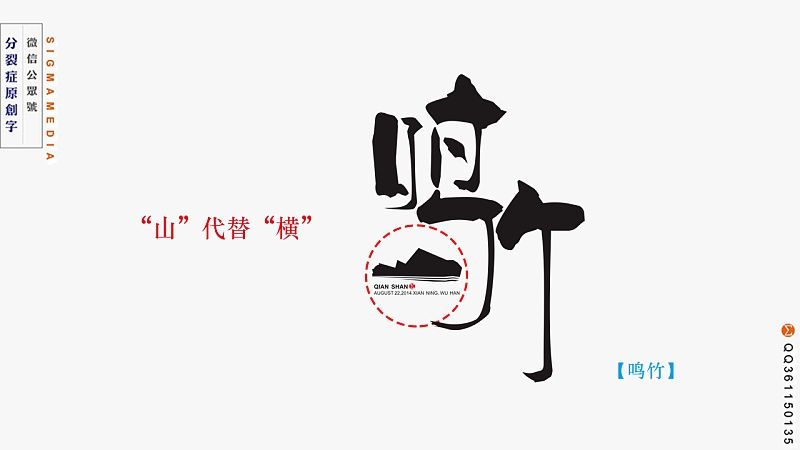
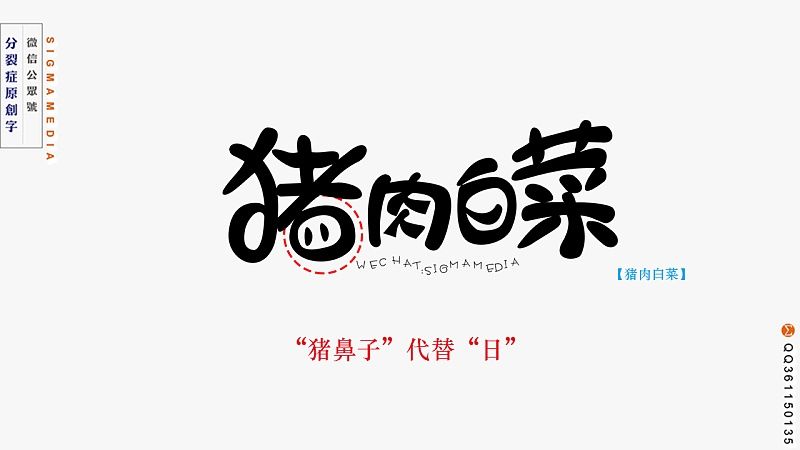
2.笔体重复
设计了几个字却感觉貌合神离很难搭在一起?这时宜用此招,笔体重复就是在几个字中都使用同一种笔体,或是找到某个视觉效果显著的特点重复用在不同的字中。
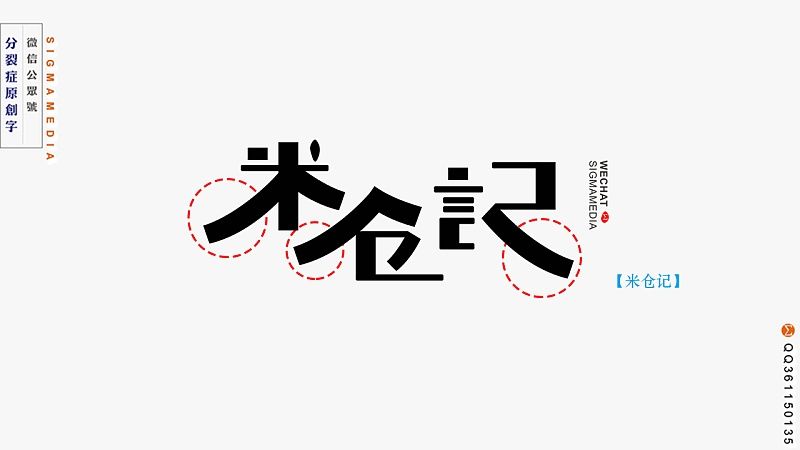
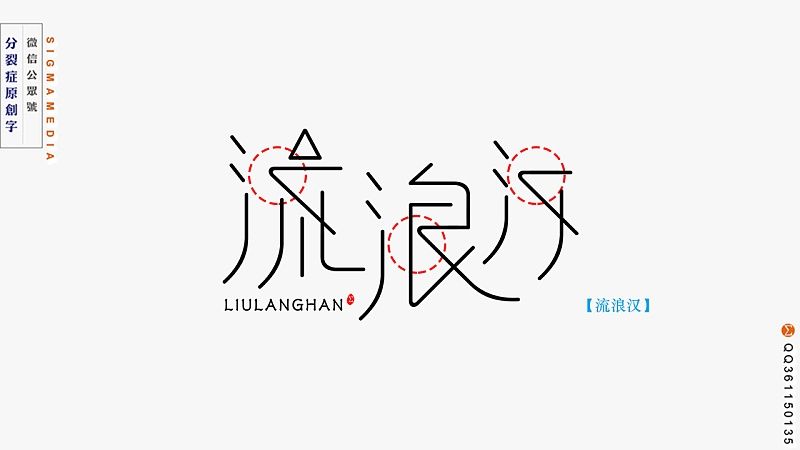
笔体重复可以让字秩序化、整齐化,整体视觉呈现出和谐统一、富有韵律的效果,这招重点是设计前先找到几个字的共同点。
3.粗细对比
都说没有对比就没有伤害,可见对比能够造成冲突,引起关注。汉字是方块字,横竖的笔画自然是非常之多,通过横变粗竖变细或横变细竖变粗,夸大横竖笔画的粗细对比能够让字风格独特出人意料。
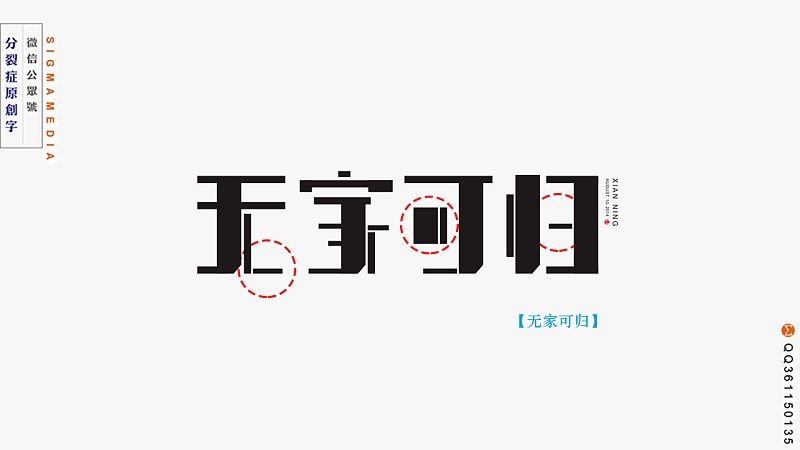
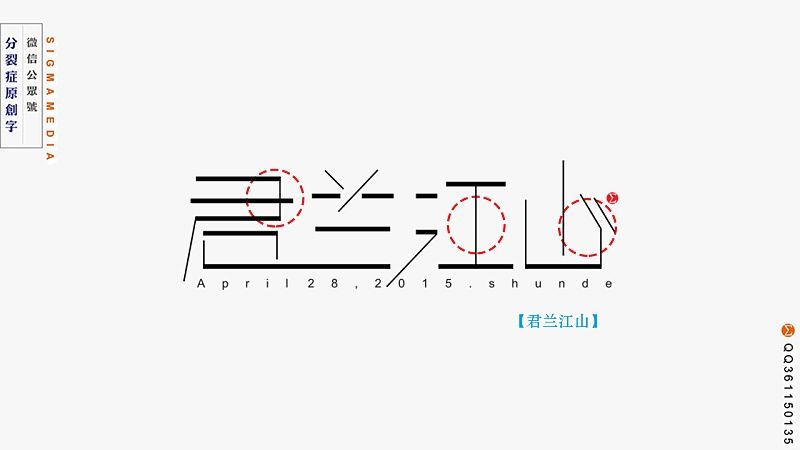
这种笔画粗细对比的手法可以让字线面相得益彰,美术特征明显,有很强的装饰性。
4.块面特异
我们日常看到的字都是横竖有别,撇捺清晰,如果故意将汉字的个别笔画块面处理,就有了突破以往认知的新奇感,增加趣味性。
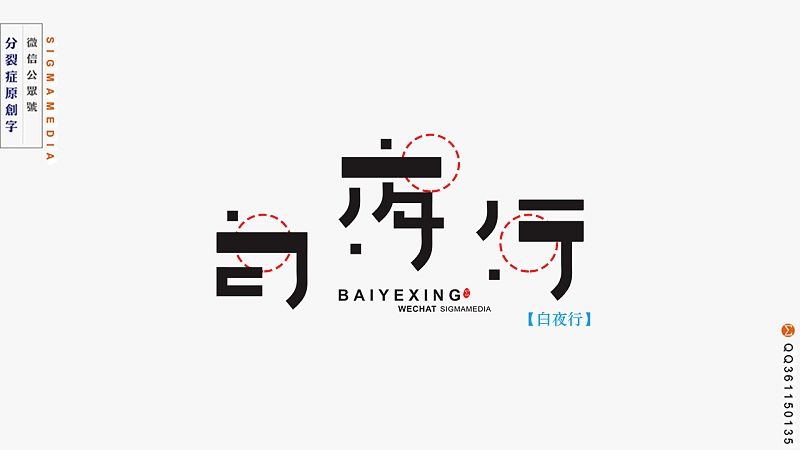
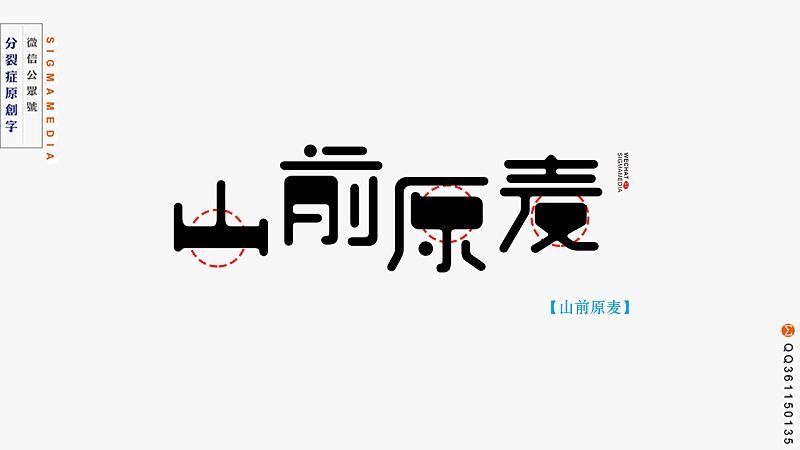
块面特异是在保证整体汉字字体规律的情况下,小部分块面与整体笔画秩序不和,造成万绿丛中一点红的效果。
5.同体共用
这种方法在《断舍离,字体设计三种思路》中聊过,同体共用就是一个字打破原有的文字结构,一个笔画代替原来的多个笔画;或者是几个字根据汉字的形态、特点等,把相邻或相近的笔画连在一起,几个字共用一个或几个笔画。
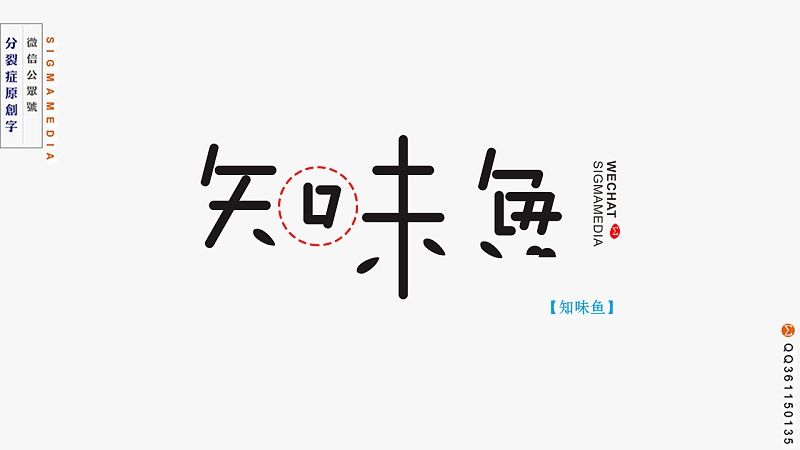
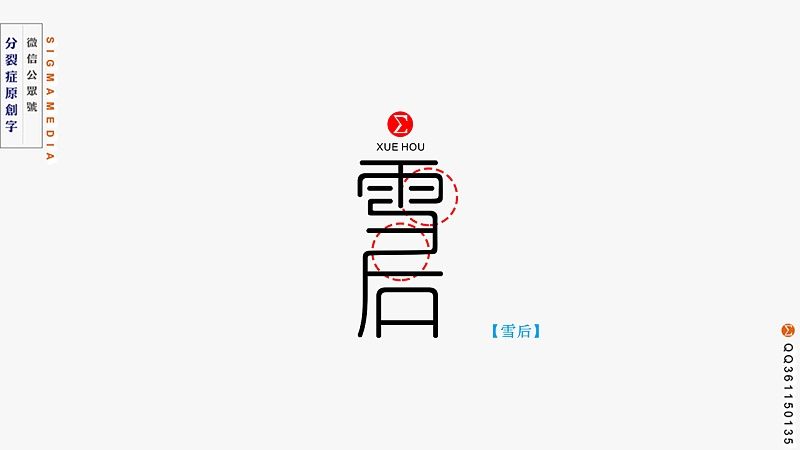
这种手法讲究笔画与笔画之间的有机连接,恰当处理能够让字简介明了、统一协调。
6.解构重组
一言不合就大卸八块,解构重组就是把汉字原有的结构分离打散,然后再重新进行组合,这种组合就是重新安排字体的疏散与紧凑、分离与散落等,让字突破常规形式感更强。
7.重心偏移
汉字之方让每一个字都张力均衡、四平八稳,这是汉字的优势,但看多了难免腻歪。通过重心偏移就可以打破这种固有印象,让字个性鲜明。
这种偏移可以是上下偏移,纤细高挑的瘦高字就属此类,也可以是左右偏移,像浑厚波折的矮扁字等。
8.符号衬托
此招其实是意象替代法的抽象升级,一方面可以用点、线、块以及字母等抽象元素替代汉字的某些笔画,另一方面也可以用线条、圆环、数学符号等侧面衬托,烘托氛围。
9.空间构成
我们字体设计都是在平面上设计的,但平面不平,可以通过多种手段营造三维感。
最常见的就是立体画面法,通过透视原理表现出字的正面和侧面,就会有三维感;另一种方法就是正负空间法,也就是图底可以在视觉上互换,参考著名的鲁兵杯。
还有一种方法就是表现阴影,当然不是简单的给字加个投影,而是只把阴影作为视觉对象,设计出阴影,让阴影之间的空白区域呈现出字体,其实这是正负空间的升级法。